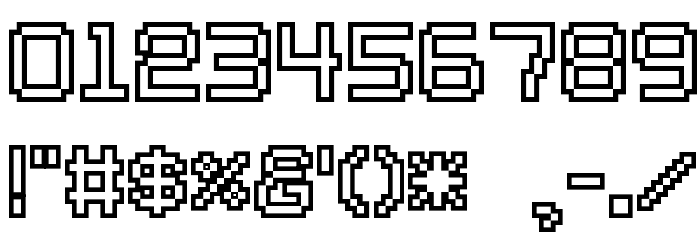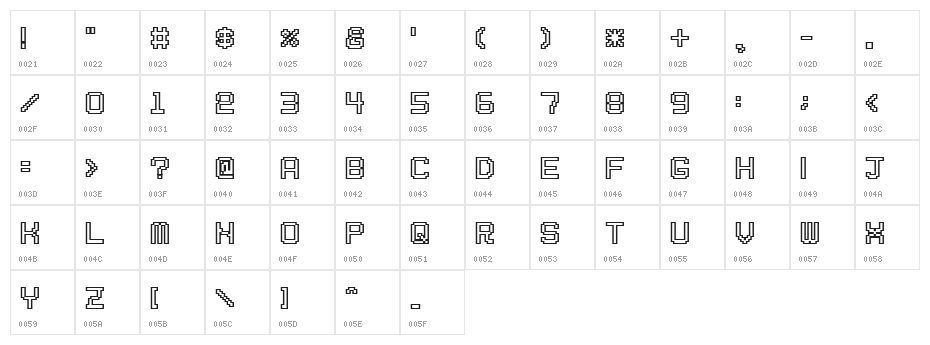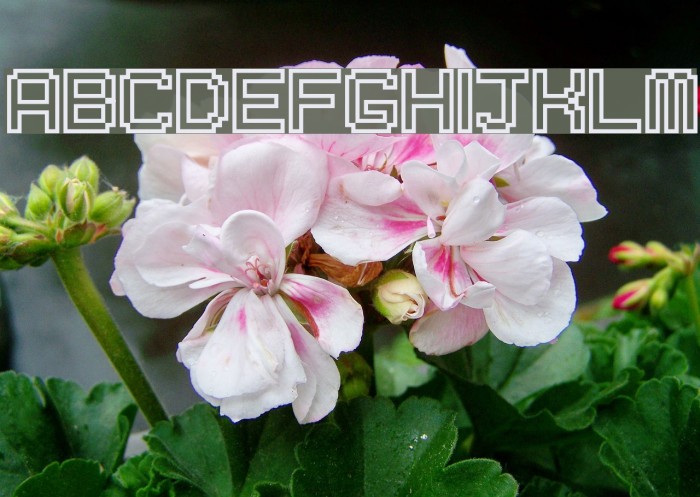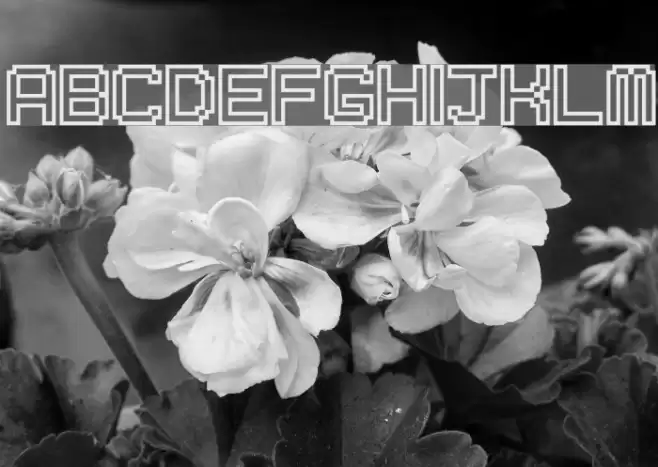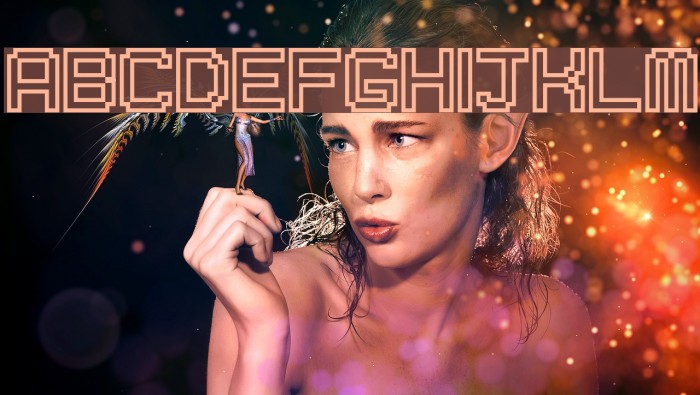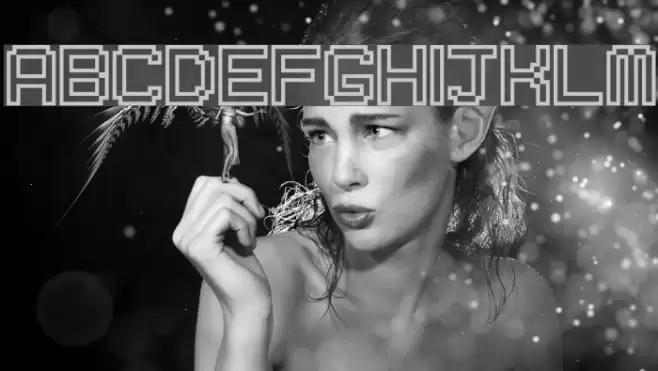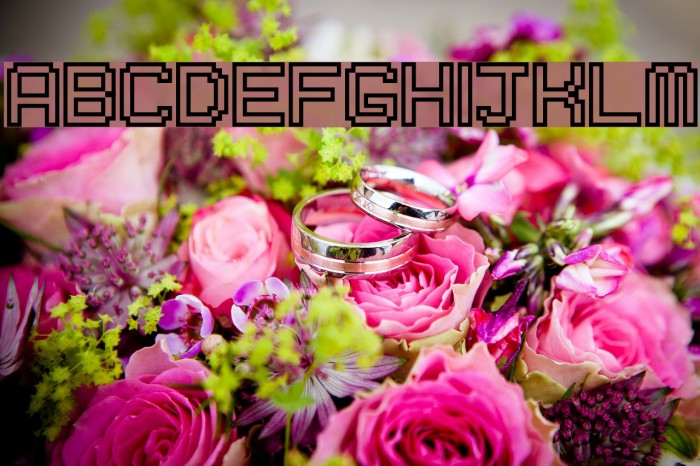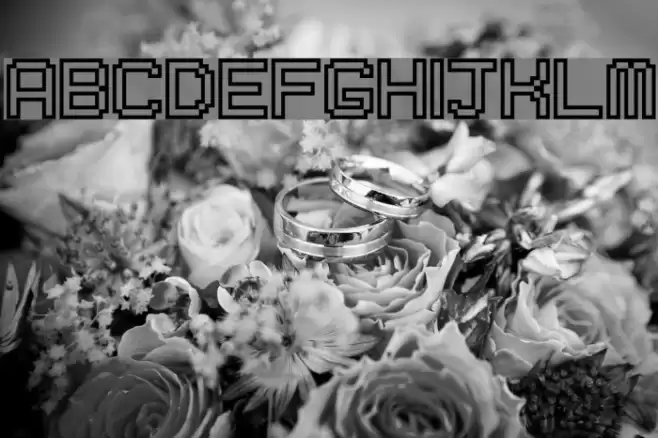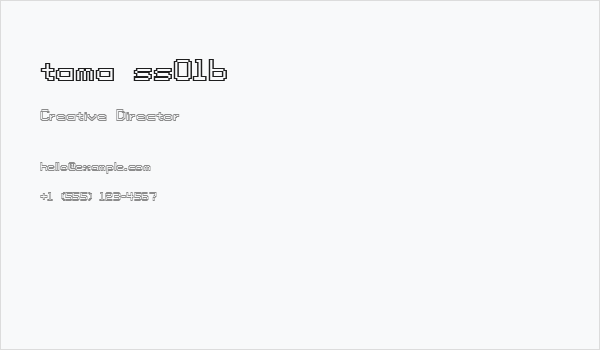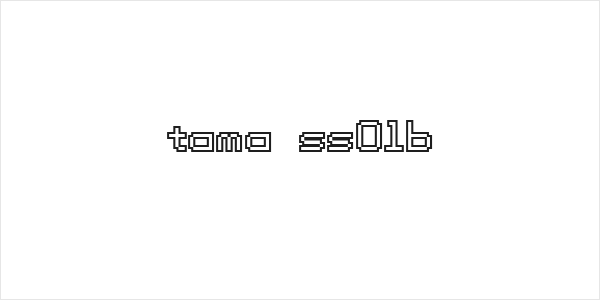
tama ss01b Font
| Gesamtstil | Vintage |
| Anwendungsfall | Logos, Headlines, Posters |
| Vorgeschlagene Projekte | Ideal for video game design, retro-themed posters, digital art, and any project seeking a nostalgic, digital aesthetic. |